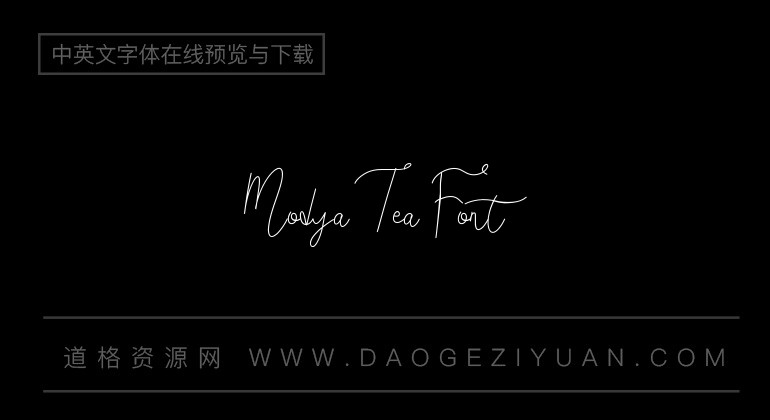
Modya Tea Font 是一款优美、自然、舒适的字体,它的设计灵感来源于中国传统的茶文化。这款字体的设计师是来自中国的设计师 Modya,他的设计风格强调简洁、自然、舒适,具有浓郁的东方美感。 Modya Tea Font 字体的特点是:字体线条流畅、自然,整体呈现出一种细腻的感觉,适合于设计师在设计茶文化、古风、文艺作品等方面的应用。这款字体是一款免费字体,可以商用,但需要注明出处。同时,该字体提供了多种字重和字形,方便设计师在不同场景下使用。 总之,Modya Tea Font 是一款极具东方美感的字体,值得设计师们尝试使用,为设计作品增添一份独特的韵味。内容介绍
Modya Tea Font是一款非常不错的手写艺术字体,具有很好的视觉感,适合于文化类的宣传设计、商业类品牌的广告和产品包装设计以及个性化文字排版等较多场景。